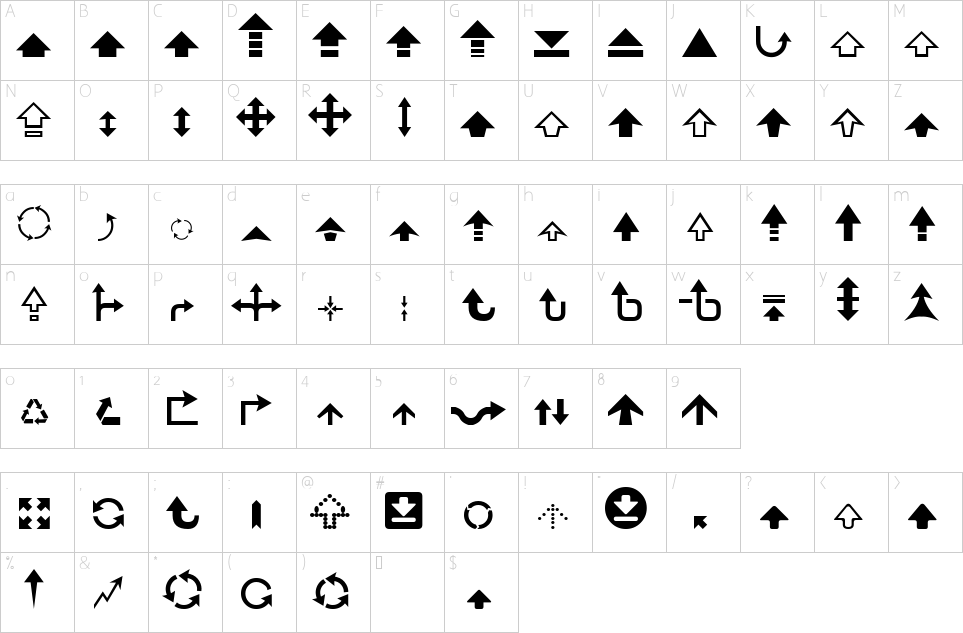
Aqui está uma descrição em português do Brasil, envolvente e natural, para a página de download da fonte ‘Arrow 7 Font’, respeitando as regras fornecidas: A fonte Arrow 7 é uma seleção elegante e moderna, ideal para design gráfico e publicidade. Ela foi projetada pela Style-7, uma equipe proeminente na criação de fontes visuais. Com sua simplicidade e precisão, Arrow 7 é fácil de usar e dá um toque único em qualquer projeto. Esta fonte foi baixada 3.656 vezes, um número que provavelmente se deve à sua versatilidade e estilo moderno. Descubra por si mesmo o encanto desta fonte, que será um complemento imprescindível em qualquer conjunto de fontes do seu projeto. Descarregue Arrow 7 agora e aproveite um design visual moderno e diferenciado.